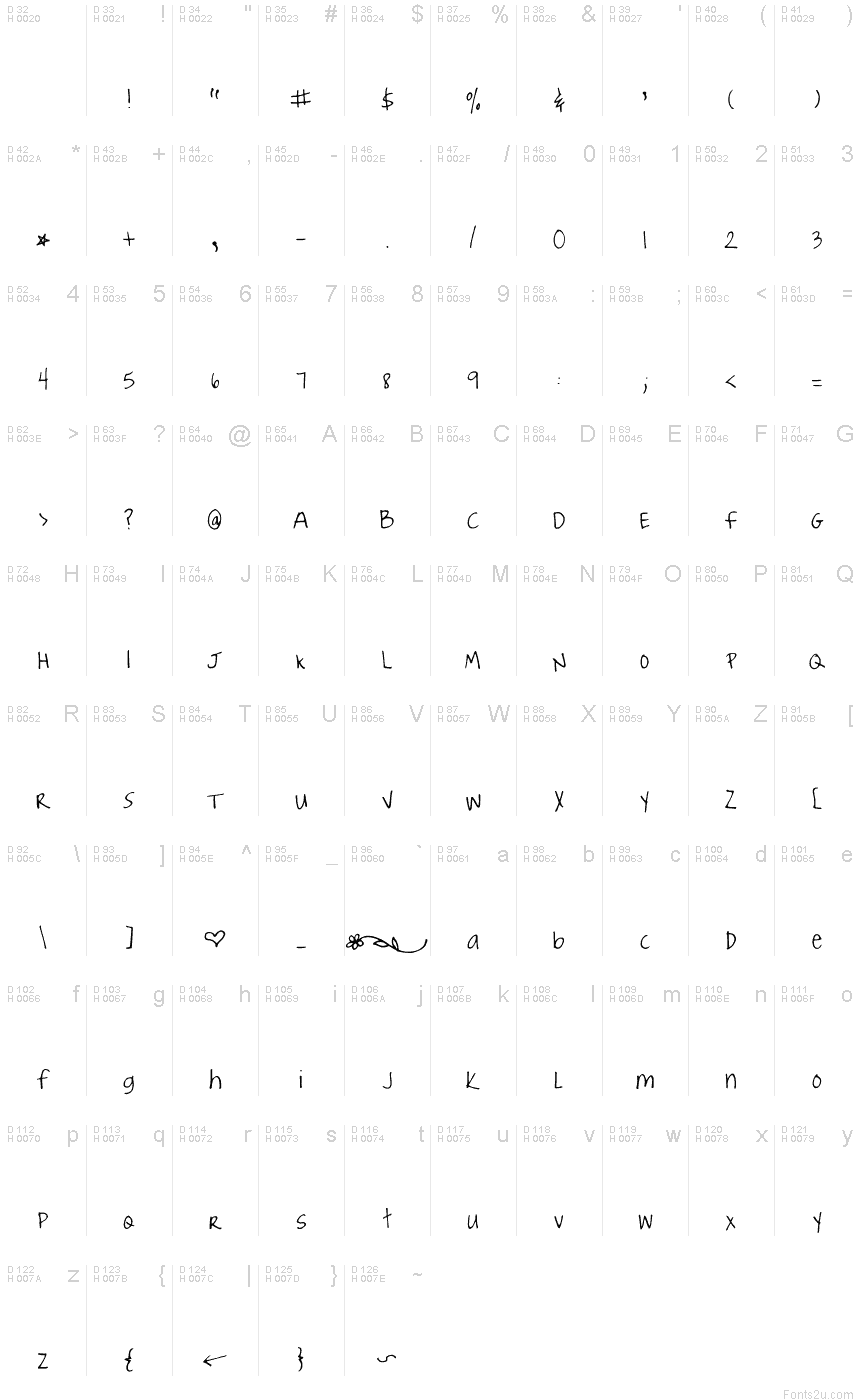
Joyful Juliana od Kimberly Geswein to darmowy krój pisma odręcznego o swobodnym, wesołym rytmie, który przywodzi na myśl szybkie pismo wykonane pisakiem. Litery opierają się na długich, rozluźnionych pociągnięciach i zaokrąglonych kształtach, a niektóre wyższe znaki wyciągają się ku górze, nadając całości żywy i nieco nieszablonowy charakter.
Świetnie sprawdza się w tytułach scrapbooków, materiałach szkolnych, swobodnych projektach opakowań, grafikach na blogi czy kartkach okolicznościowych – wszędzie tam, gdzie darmowy font o tak przyjaznym charakterze ma sprawiać wrażenie osobistego, nie stając się przy tym zbyt skomplikowanym. Użyj go, gdy chcesz, aby krótkie nagłówki, etykiety, teksty na okładkach czy cytaty wyglądały nieformalnie i „po ludzku”, ponieważ nierówne wysokości i otwarte kształty sprawiają, że tekst wydaje się lekki.